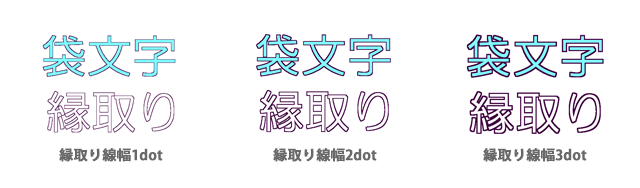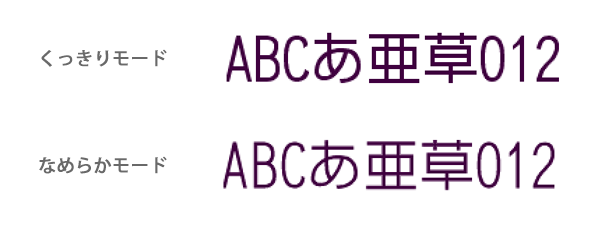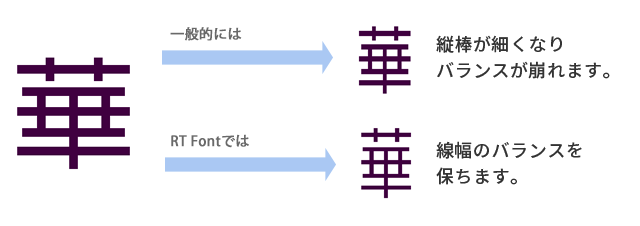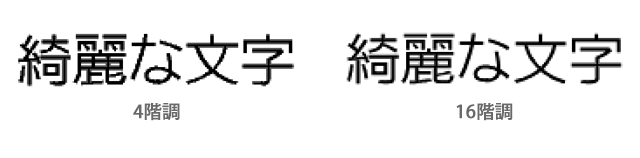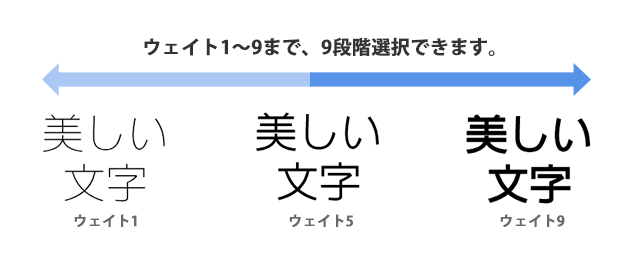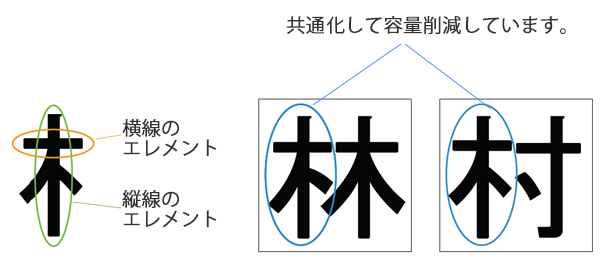
RT Font(スケーラブルフォント)
RT Fontとは?
スケーラブルフォントの中でも、TrueType Fontと違い組込み向けの低容量フォントになります。
RT Fontは当社独自形式ですので、他社のフォントとの互換性はありません。
TrueType Fontはフルアウトラインですが、RT Fontはデータがエレメント(部品)で構成されています。
「横線」「縦線」「右払い」などのエレメントですべての文字を表現しますので、漢字の部首などを共通化することでデータ容量を抑えることができるのです。
TrueType Fontの場合
RT Fontの場合
エレメント
ウェイト調整
1つのフォントファイルのみで、線の太さ(ウェイト値)を調整できます。
ウェイト調整
縁取り
展開文字データを縁取り文字へ変換し、背景色(画像)との親和性を高めることができます。
縁取り線幅の調整も可能です。
縁取り
描画モード選択
直線に対してグレースケール描画をしない「くっきりモード」と直線に対してもグレースケール描画する「なめらかモード」を選択できます。
描画モード選択
線幅保持(くっきりモードのみ)
縦長、横長で表示した場合でも縦線横線の線幅のバランスを保ち、文字デザインを崩さず表示できます。
線幅保持
アンチエイリアス(グレースケール)
4階調、16階調のグレースケール描画により、文字をより滑らかに表示できます。
階調数が少ない方が処理速度が速いです。
4階調、16階調のグレースケール描画
回転
展開文字データを1度刻みに回転させることができます。
回転
斜体
展開文字データを1ドット刻みで、フォントの上部をずらすことができます。
斜体
128×128dotの例
描画した文字画像(展開文字データ)をメモリに保持し、次回の描画時はラスタライズせずにメモリから直接呼出し、高速に描画することができます。
ビットマップフォント置換え
10、12dotのような極めて小さな文字サイズでは、サイズ毎に字形が最適化された ビットマップフォントを内包することで
可読性を損ないません。
※ビットマップ置換え機能を利用する場合は、ビットマップフォント内包分のファイル容量が増えます。
スケーラブルフォント
画像:TrueTypeFont
置換えられたビットマップフォント
画像:置換えられたビットマップフォント
ラスタライザーとレイアウトエンジン
RT Fontなどのアウトラインフォントは、フォントファイルのみでは文字表示されません。
ラスタライザーというフォントデータを文字画像に展開するソフトウェアが別途必要になります。
ラスタライザー
ラスタライザーで画像化された1文字ずつの画像を文字列にします。
文字間や行間の間隔調整、文字列の回転などさまざまな処理もできます。
アラビア語やタイ語など複雑な表記ルールを持つ言語を正しく表示するために必要なソフトウェアです。
レイアウトエンジン